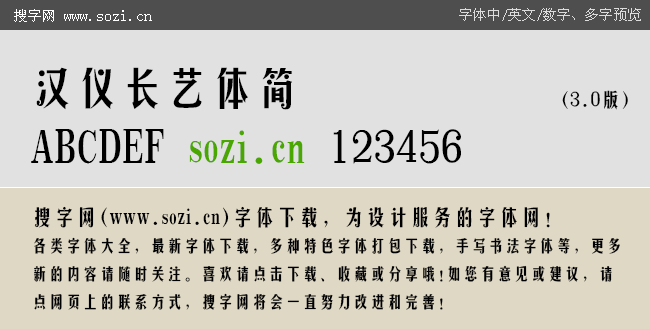
漢儀長藝體簡
搜字網(wǎng)給大家提供一款漢儀長藝體簡中文藝術(shù)字體下載。漢儀長藝體筆畫既有黑體的粗壯醒目,又有宋體的秀美柔和,加上藝術(shù)性的圓球形點(diǎn)、起筆如蝌蚪形的頓點(diǎn)、螺螄轉(zhuǎn)似的小鉤,配以修長的字形,如少女般婷婷玉立,裊娜動(dòng)人,美觀而不落俗套。適合標(biāo)題、廣告、兒童讀物使用。